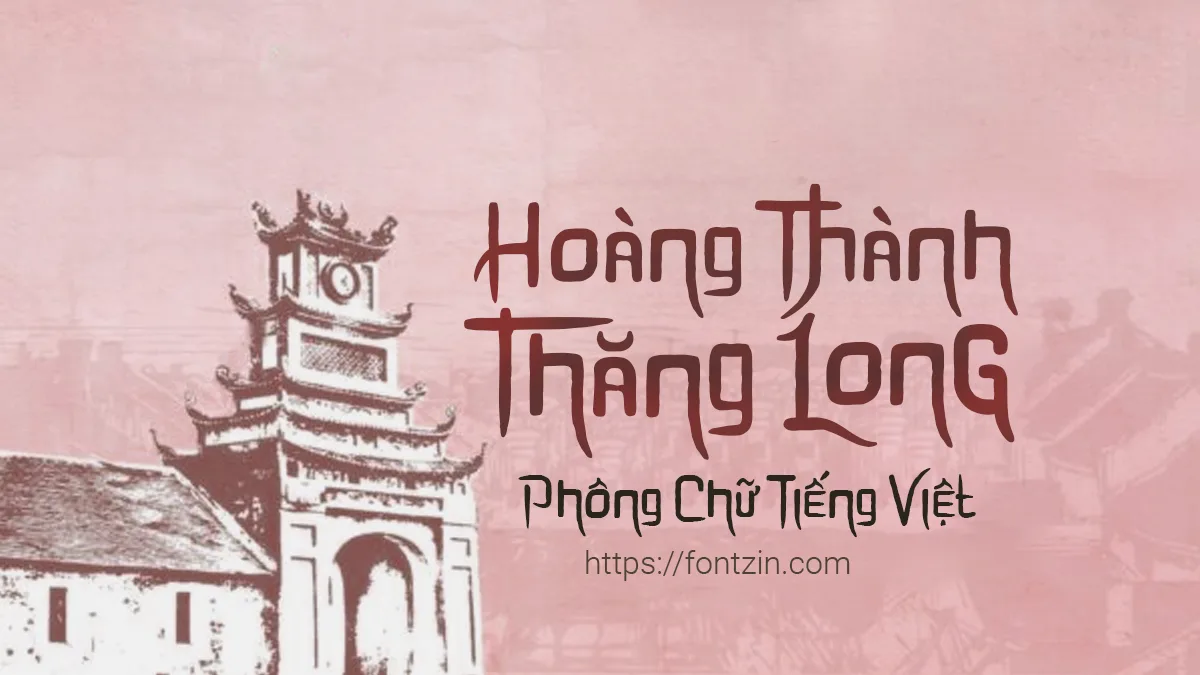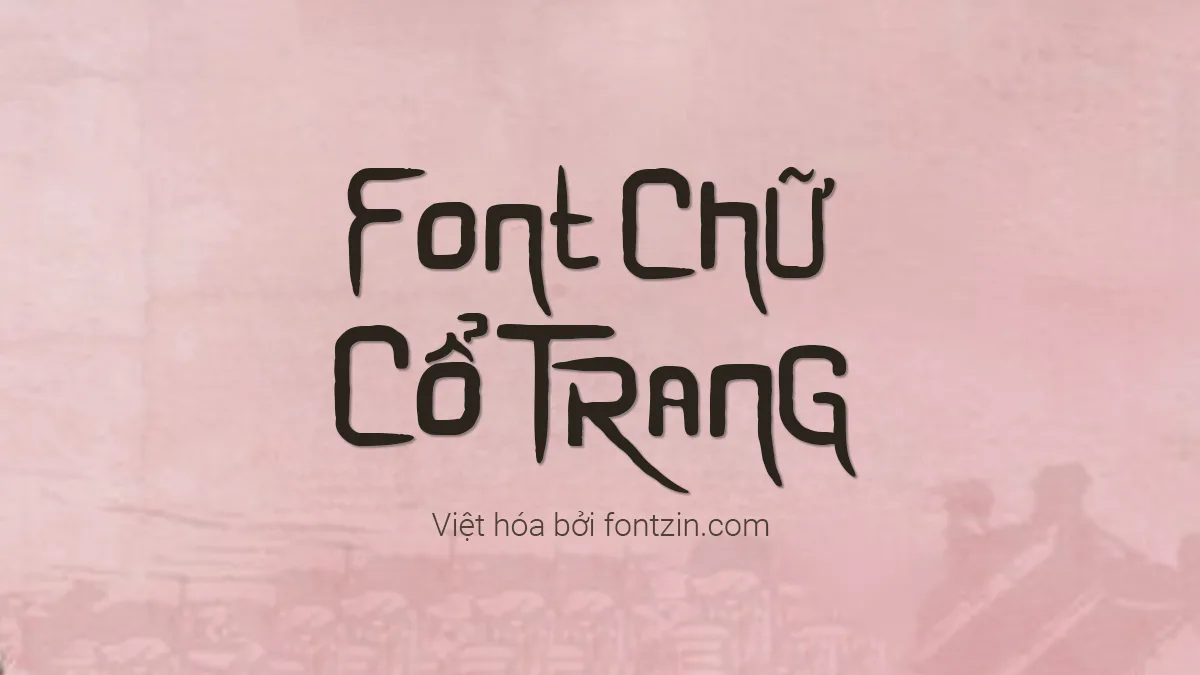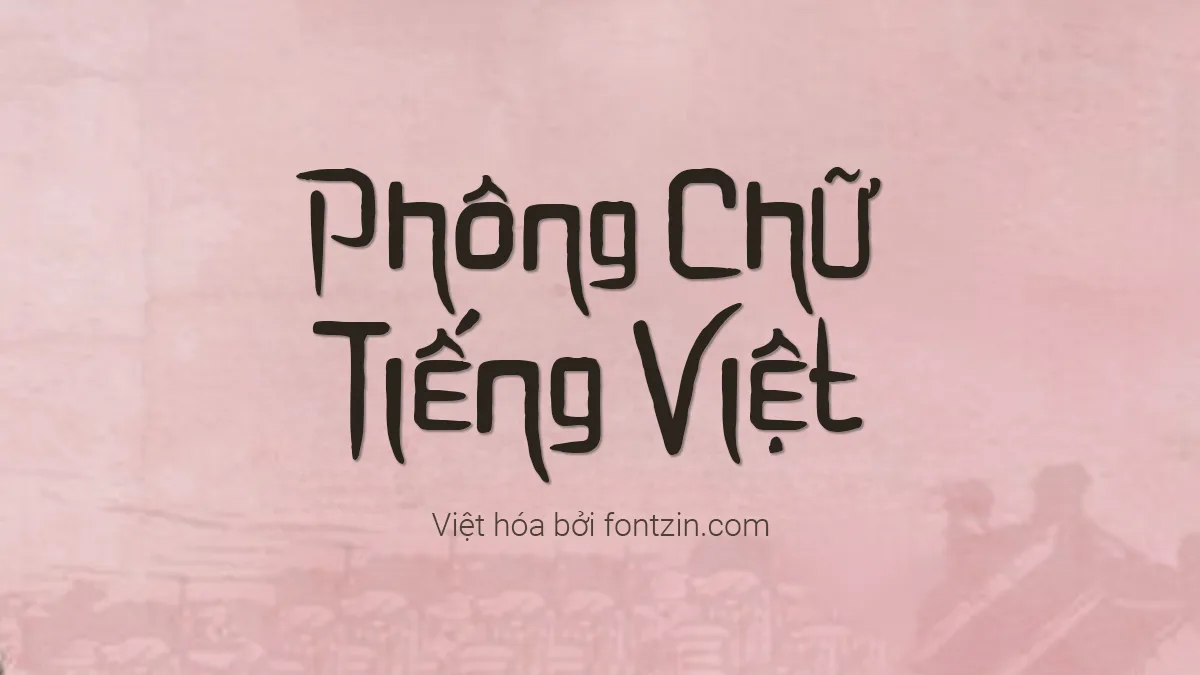
Font Việt hóa Jujutsu Kaisen
Tải Font Việt hóa Jujutsu Kaisen – Phông chữ Cổ trang, truyện tranh
Font Jujutsu Kaisen, được tạo ra bởi tác giả và họa sĩ minh họa Gege Akutami, đã được FontZin Việt hóa để bổ sung các ký tự tiếng Việt, giúp người dùng dễ dàng sử dụng trong các thiết kế của mình.
Mang đậm phong cách Nhật Bản, font chữ này đem đến một sự mới mẻ cho thiết kế đồ họa. Với các đường nét phá cách, linh hoạt nhưng vẫn giữ được vẻ cổ điển, font Jujutsu Kaisen tạo nên sự hòa quyện giữa hiện đại và truyền thống. Đây là lựa chọn lý tưởng cho các thiết kế bìa sách, truyện tranh, poster và những ấn phẩm đậm phong cách cổ trang.
Những điểm nổi bật trong font Việt hóa Jujutsu Kaisen:
• FontZin đã thiết kế lại bộ dấu để phù hợp với tiếng Việt mà vẫn giữ được nét đặc trưng của font chữ.
• Thêm và chỉnh sửa một số ký tự để hiển thị dấu tiếng Việt một cách chuẩn xác hơn.
• Điều chỉnh Kerning để tránh hiện tượng dính dấu.